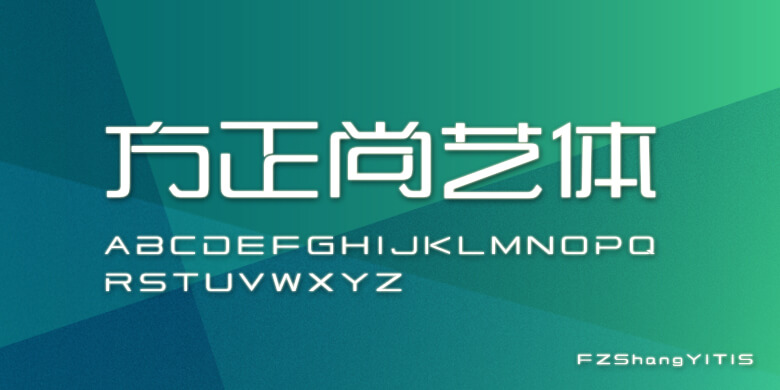
方正尚艺体-简繁
品牌:方正字库设计师:李诗德发行时间:2018字库编码:简繁扩展(GBK)、大陆简体(GB2312-80)分类:创意字体
作者李诗德,自从事平面设计行业十余年来,接手过太多的企业标准字设计,在一次偶然的企业标准字设计过程中,脑中突然灵光一闪,为何不自己做一款字体,于是在经历了一番长久的摸索和设计之后,就有了现在的这款方正尚艺字体。
字体秉承中国字的方正之道,笔画在黑体直来直往的基础上进行圆角设计,给人视觉不失黑体的力道,又具备圆体的圆滑柔和,从而在不影响字体阅读性的同时又增加字体的观赏性。字型结构融合了篆体的饱满和平稳,进而简化变形处理,时尚、简洁、整齐、美观,字体种的断笔处理,让许多拥挤的部件视觉上显得更加疏朗。
这款融合艺术性和时尚性的尚艺字体,适合各种行业的应用,例如电商平台、金融、汽车、广告、地产、电子产品等许多行业;适用于海报、包装、企业名字、企业标准字、画册等各种广告的设计应用。